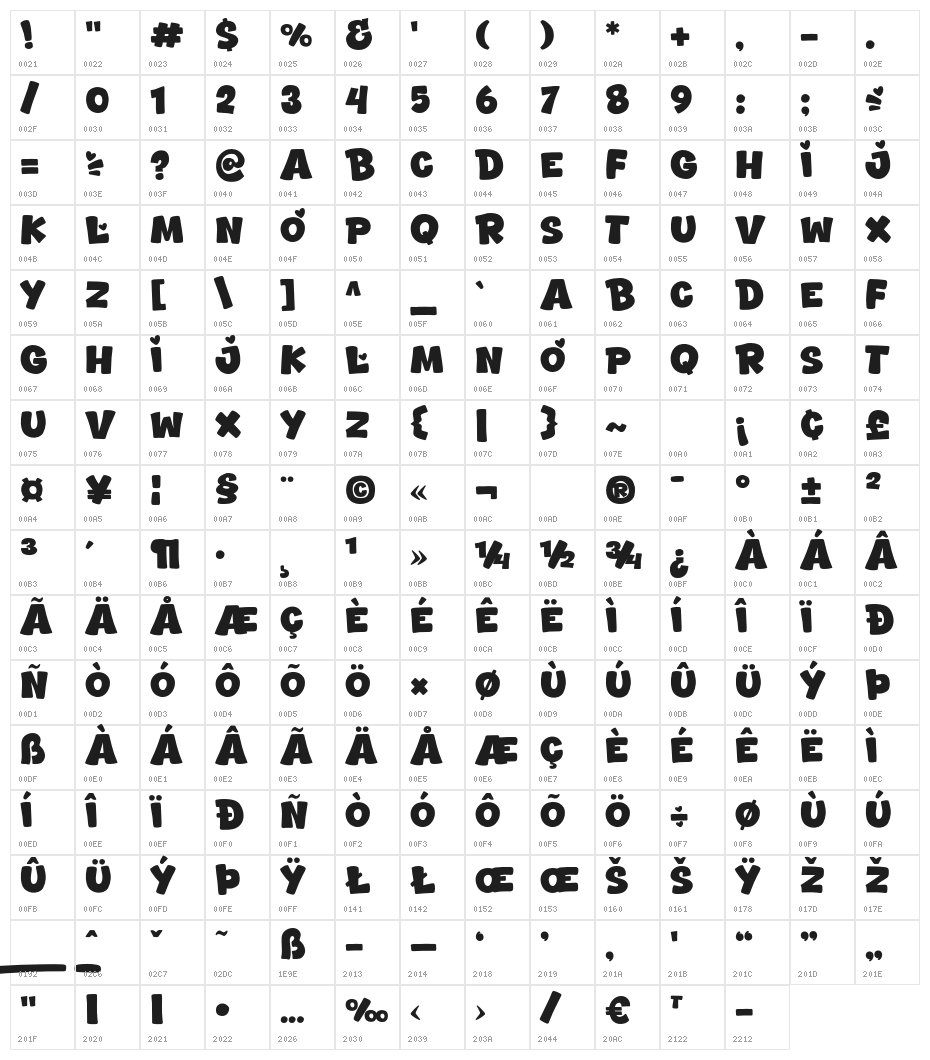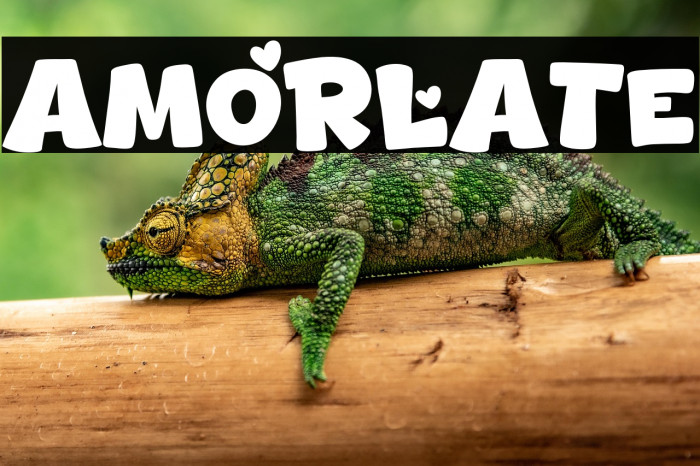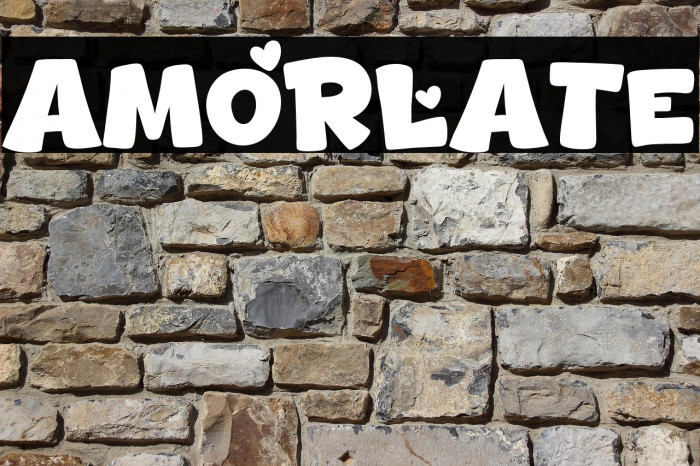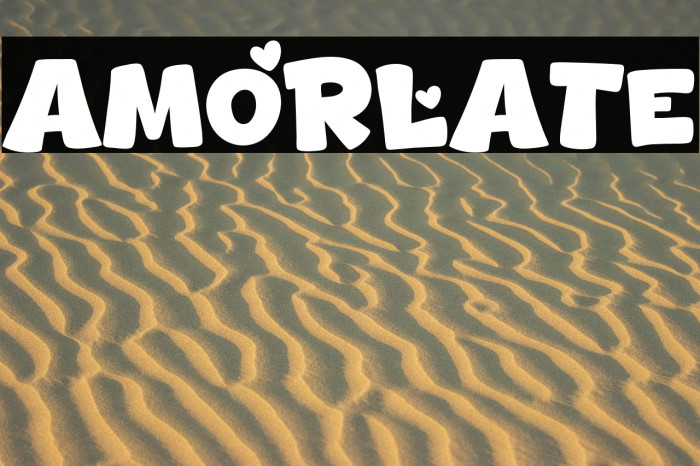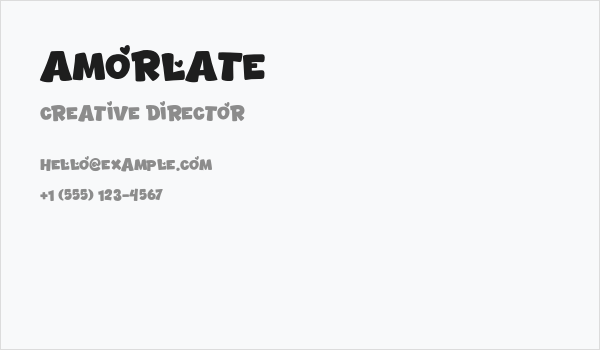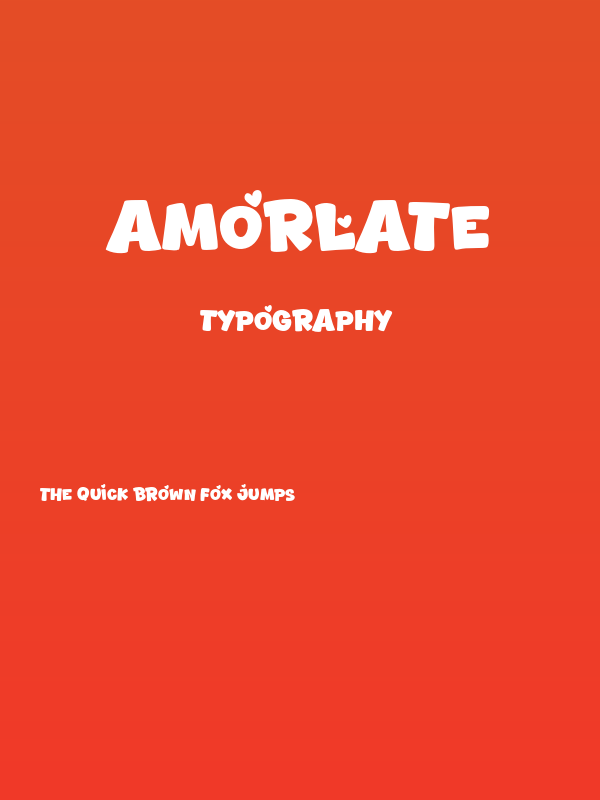
Amorlate Font
| Gesamtstil | Playful |
| Anwendungsfall | Logos, Headlines, Posters |
| Vorgeschlagene Projekte | Ideal for children's books, greeting cards, playful branding, and social media graphics. |